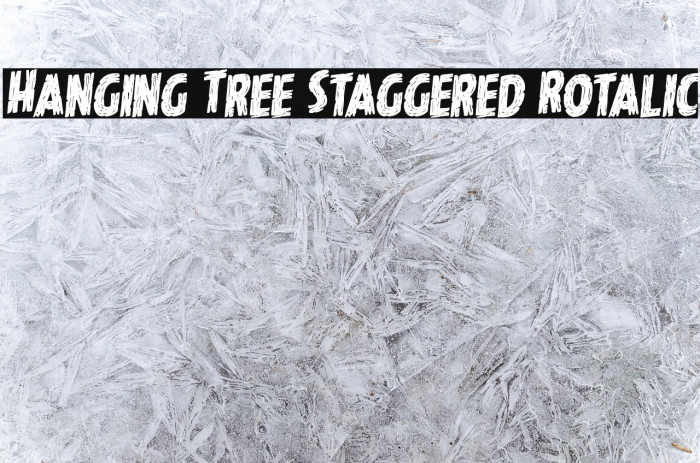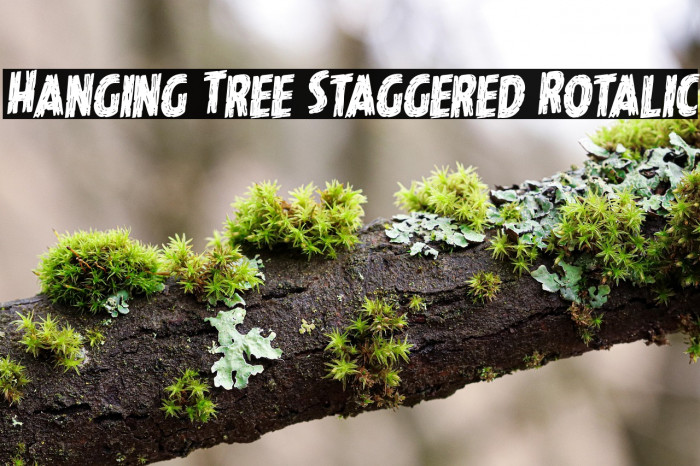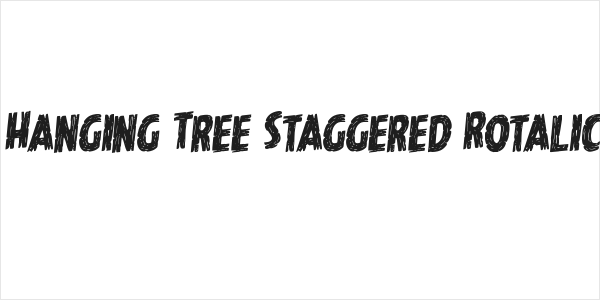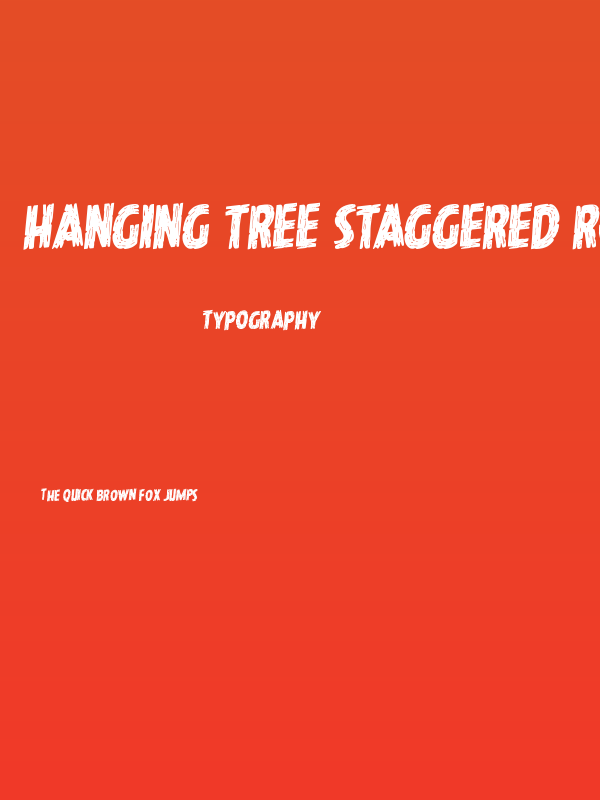
Hanging Tree Staggered Rotalic Font
✎ Messy
| 推荐项目 | Ideal for projects that require a creative and energetic touch, such as posters, album covers, or branding for artistic ventures. |